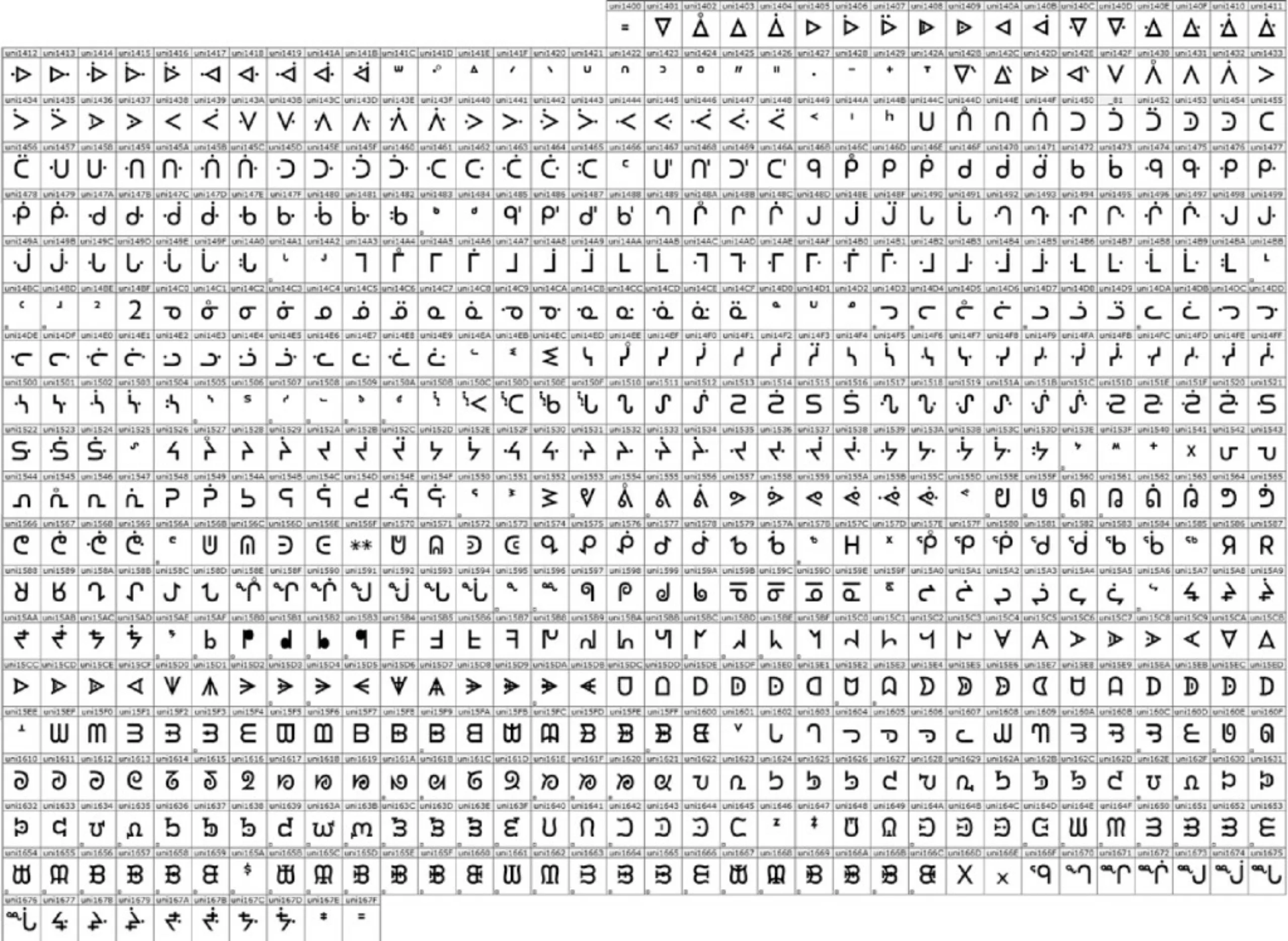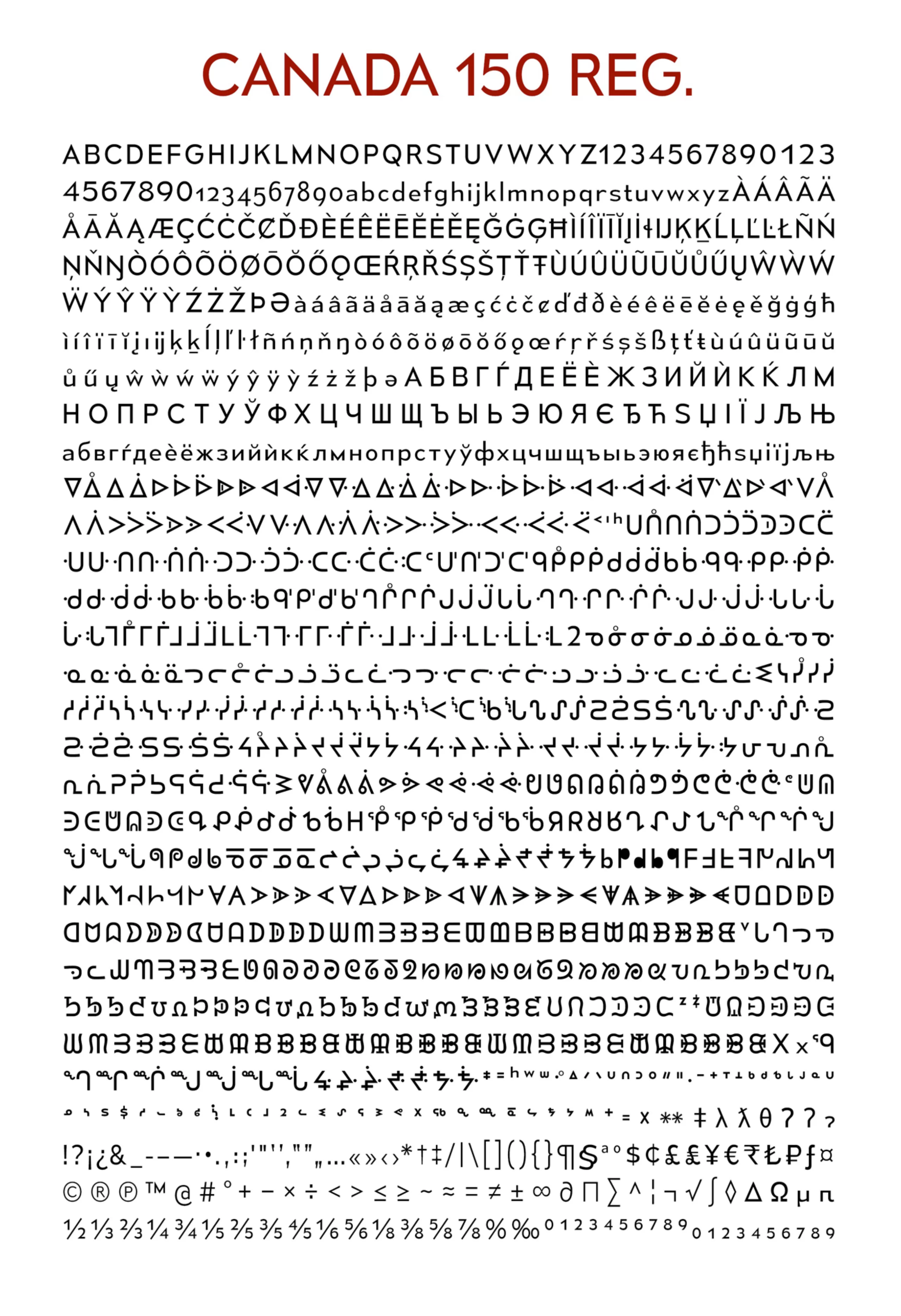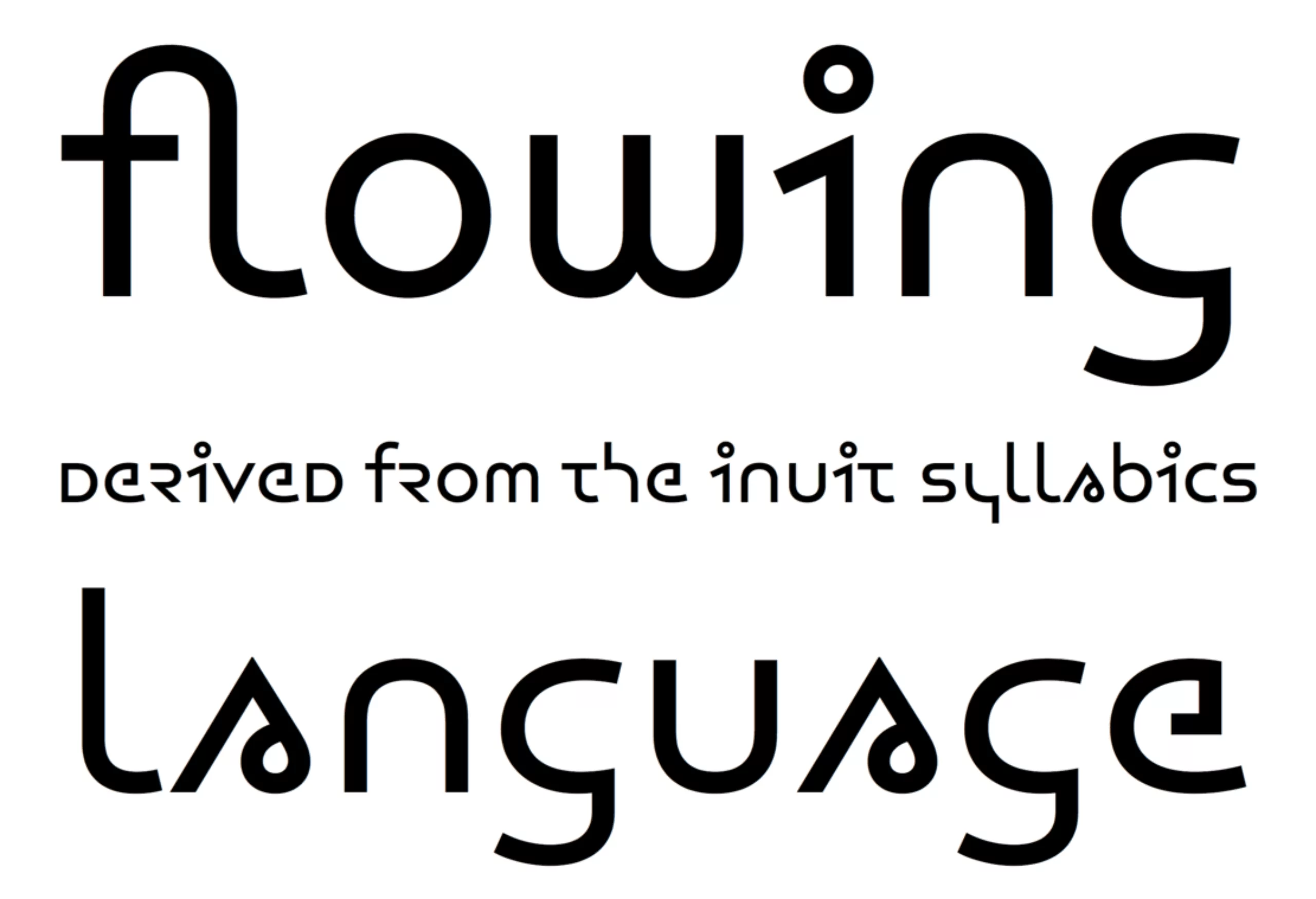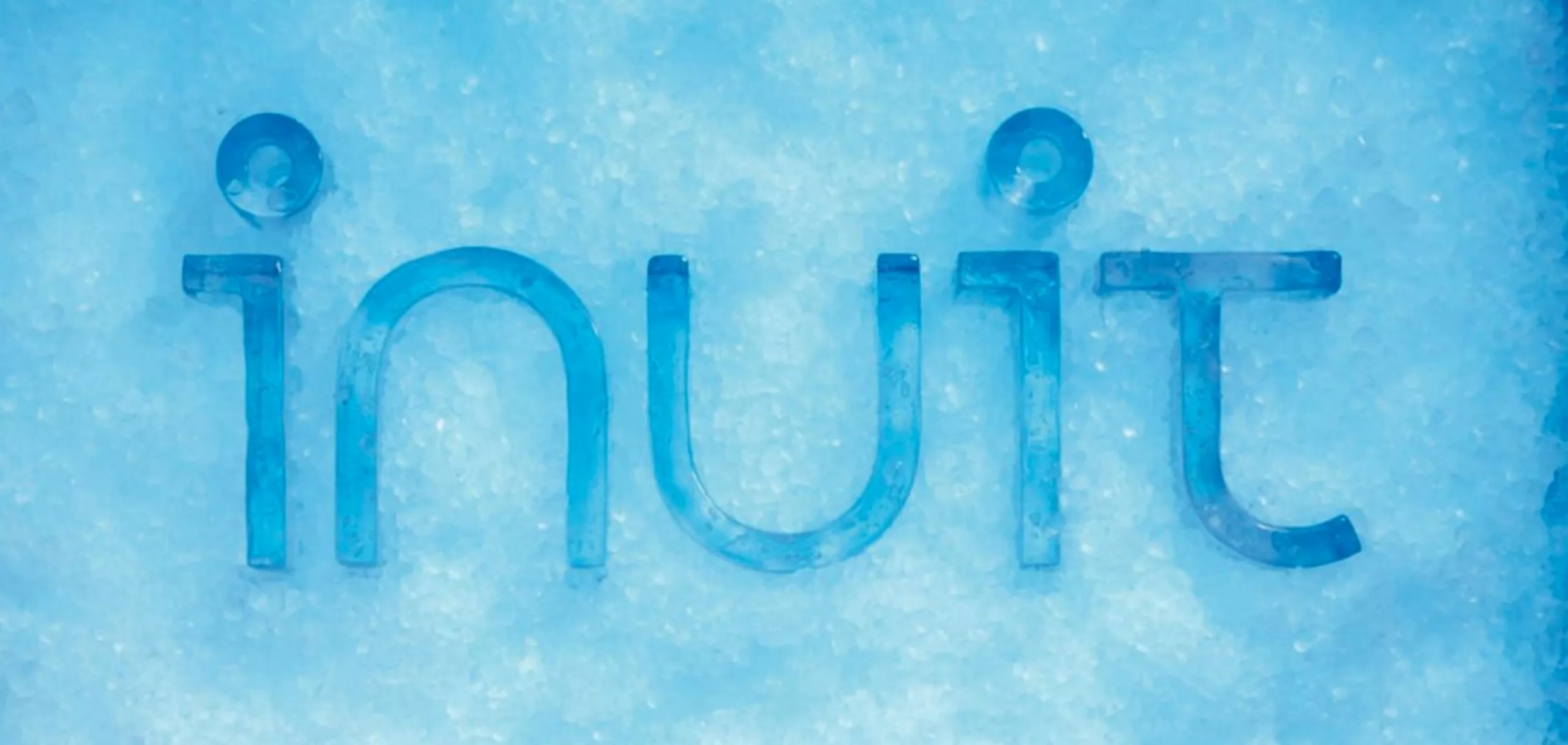
Une typo qui sent bon le castor
En 2017, nos amis canadiens fêteront les 150 ans de leur pays. En réalité, les 150 ans de la Confédération Canadienne, car c’est en effet en 1867 que les dirigeants des colonies du Canada-Uni, du Nouveau-Brunswick et de la Nouvelle-Écosse ont décidé de s’unir pour ne former qu’une seule et même nation (celle-là, vous pourrez la replacer dans les dîners mondains, elle fait toujours son petit effet).
Pour célébrer cet anniversaire, le Canada est en train de mettre les petits plats dans les grands, et déploie au fur et à mesure une identité visuelle dédiée à ce jubilé. Cela a commencé avec un logo issu d’un concours remporté par Ariana Cuvin, une étudiante en commerce international et arts numériques à l’Université de Waterloo.
Lors de sa présentation, le logo n’a pas fait l’unanimité auprès des designers à travers le monde. Il a même subi de terribles critiques un peu partout sur la toile, au point d’être même classé parmi les 10 pires logos de l’année sur le site BrandNew.
Enfin, là ce n’est pas le propos.
Joyeux sesquicentenaire !
En plus d’un logo pour célébrer ce sesquicentenaire (du latin sesqui -une fois et demi- tenez, encore une à replacer dans votre dîner mondain histoire de susciter l’admiration), le Canada a voulu marquer le coup en adoptant une police de caractère unique et surtout unifiée. Une grande première, puisqu’en effet, mis à part l’anglais et le français, les deux principales langues du pays, on y retrouve également les signes des langues indigènes canadiennes, comme l’inuktitut, parlée par près de 30 000 inuits.
Oui, il faut savoir (si jamais votre conversation à table tourne beaucoup autour du Canada) qu’il existe onze langues officielles là-bas.
Mais à la base, ce n’était pas prévu comme ça : enfin je vous explique.
Le secrétariat fédéral chargé de mettre en place tout ce qui touche à cet anniversaire s’est dit “Tiens, en plus du logo, on va proposer une typo nationale, que tous les Canadiens pourront utiliser gratuitement. Un peu comme la commande publique qu’avaient fait les Français en 2014 (souvenez-vous, l’Infini commandée par le CNAP et conçue par Sandrine Nugue), sauf qu’on va d’abord regarder ce qui existe déjà sur DaFont.”
Evidemment, ils regardent du côté des typographes canadiens, et tombent sur Mesmerize, une typo conçue par Ray Larabie, un designer originaire de la capitale Ottawa, dont les plus de 300 polices gratuites sont connues et reconnues, par exemple la Pricedown, qui a servi pour le logo des jeux GTA, ou encore la Kleptocracy ou l’Euphorigenic qui ont servi aux précédents logos d’ActuLogo (bon, OK, peut-être pas les plus connus).
Donc Mesmerize leur plait. Beaucoup. Tant qu’il envoient un mail à Ray Larabie pour lui demander s’il accepterait que sa typo soit renommée et intégrée au nouveau logo du 150e anniversaire. Ray, qui avait trouvé excellent ce logo, a donc tout de suite accepté, en proposant non seulement de céder l’exploitation gracieusement, mais aussi de la modifier légèrement afin de la rendre plus unique, tout ça sans réclamer un seul dollar canadien, juste pour l’amour de son pays et la fierté de contribuer à l’identité visuelle du jubilé.
Et sa proposition a quelque peu surpris : le bonhomme, qui vit au Japon depuis 2008, a en effet proposé une modification de taille : inclure tous les caractères des langues indigènes encore parlées au Canada. Car quitte à avoir une typo universelle pour tous les habitants du pays, autant qu’elle soit la plus exhaustive possible.
Ils acceptent avec réserve, car il faut se consulter avant. Larabie ne va pas attendre, sachant les lenteurs de la bureaucratie, et va donc commencer de longues recherches en ligne pour se renseigner correctement sur ces caractères inuits et autres, en observant des dessins, des manuscrits, etc…, puis va les dessiner dans le même esprit que la Mesmerize. Son expérience japonaise lui servira puisque de nombreuses différences typographiques lui rappelleront l’écriture katakana nippone, dont notamment des styles d’écritures non linéaires et non horizontales. Le secrétariat fédéral va ensuite les envoyer à des experts pour approbation, mais ces derniers ne répondront jamais. Tant pis, on fait confiance à Larabie et on annonce la naissance de la “Canada 150”, la typographie unifiée du Canada, disponible gratuitement à qui la veut.
Concernant la typo en elle-même, la Mesmerize (pardon, la Canada 150) est un classique sans empattement.
Un beau geste de la part de ce designer qui m’a confié par ailleurs prévoir une mise à jour, suite à une erreur repérée dans l’alphabet cri.
Un autre caractère inouï(te) !
Cette histoire de typographie “Inuit” ne manque pas de nous rappeler un autre projet sur le sujet. C’est un projet qui date des années 2006-2007 il me semble.
Inuit c’est deux choses à la fois. C’était une gamme de papier Arjowiggins. Mais c’était surtout un caractère typographique gratuit dessiné Jeremy Tankard ( à demander auprès d’Arjowiggins en écrivant à cette adresse helpcenter@arjowiggins.com ). Jeremy Tankard, son nom ne vous parle peut-être pas, mais c’est le dessinateur du Bliss ou encore du Corbel, l’un des caractères fourni avec Windows Vista !
Jeremy a développé une collection de dessins de lettres dont l’inspiration mélange l’alphabet Inuktitut et l’alphabet latin afin de créer un caractère équilibré, harmonieux, et surtout lisible. Certaines des formes de l’alphabet Inuktitut sont apparues trop extrêmes pour être lisibles, et il a fallu alors développer des caractères alternatifs permettant de varier les lettres selon les usages. En plus de ces caractères alternatifs et des symboles usuels, Jeremy a également dessiné des magnifiques ligatures !
Bref, ce caractère est un véritable voyage typographique ! Il vous faudra juste mettre des moufles pour composer vos textes !